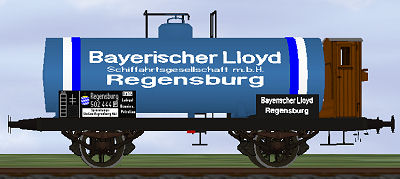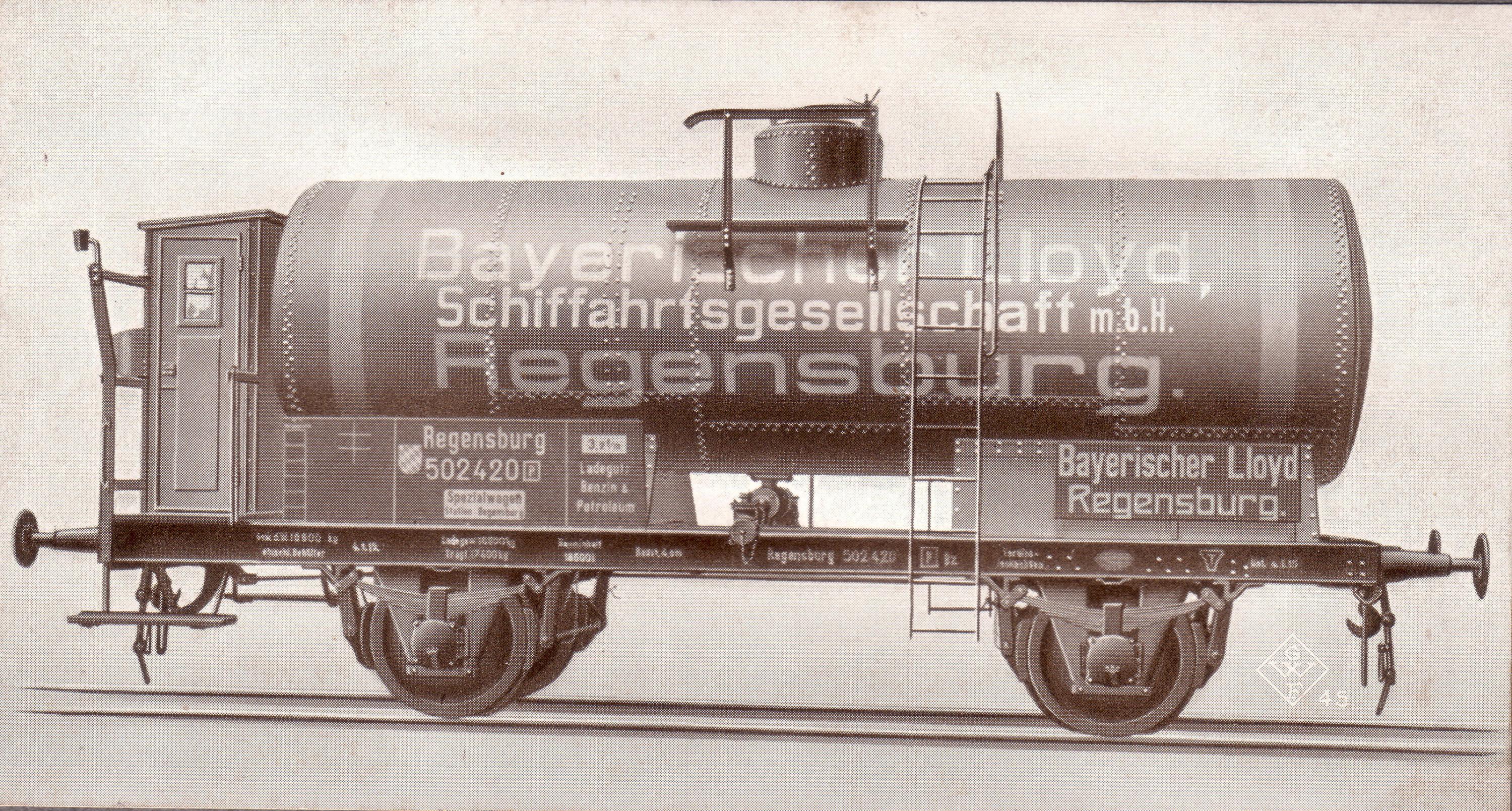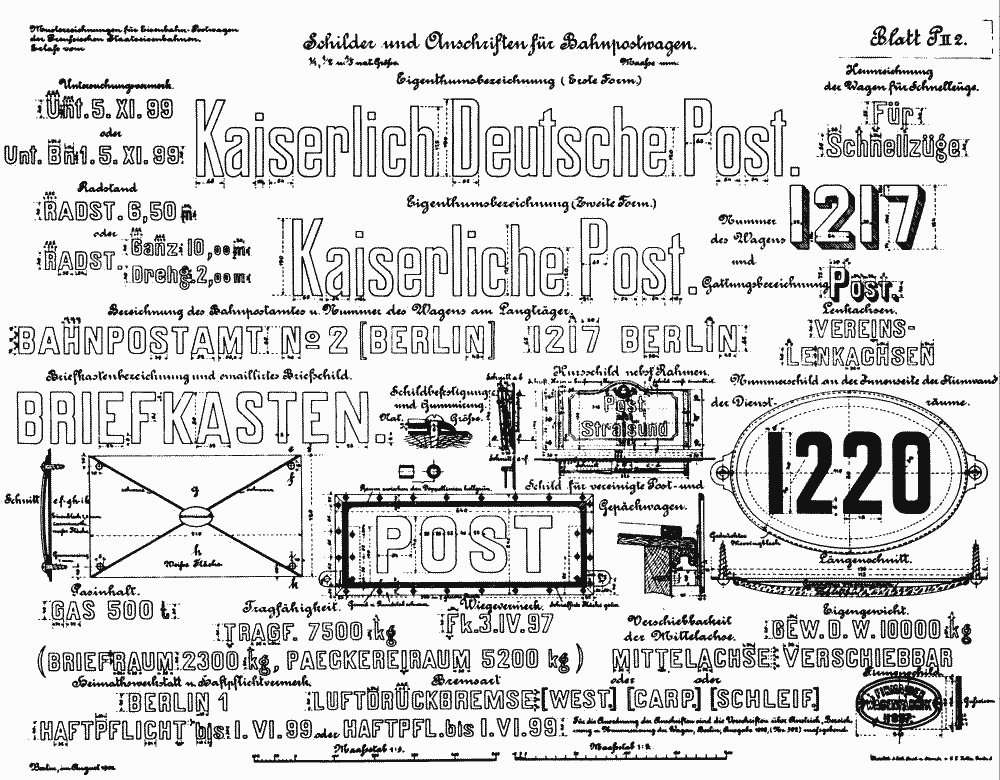
Schriftarten auf Kesselwagen der Bayerische Lloyd , ca. 1920(?)
kann mir jemand bei der Identifikation der verwendeten Schriftarten auf dem abgebildeten Kesselwagen behilflich sein? Bei den Beschriftungen am Rahmen und dem linken Stehblech unterhalb des Kessels tippe ich auf DIN1451, der Kessel selbst und das rechte Stehblech sind jedoch mit mindestens zwei unterschiedlichen Schriftarten versehen, die ich nicht identifizieren kann. Bei der oberen hatte ich Franklin Gothic vermutet, dort passt jedoch das r und einiges Andere nicht. Ich würde mich sehr freuen, wenn mir hier jemand weiterhelfen kann!
Für solche Anschriften auf Bahn-Fahrzeugen wurden damals Musterzeichnungen von Grafikern angefertigt, und als verbindlich festgelegt. Schildermaler mussten dann im Rahmen des damals technisch möglichen diese Vorlagen auf die Fahrzeuge übertragen.
Eine solche Musterzeichnung sah dann so aus:
Leider sind die meisten dieser Musterzeichnungen verloren gegangen, Möchte man also die Schrift doch digitalisieren, bleiben nur die vorhandenen Abbildungen und oft ein gehöriges Maß an Phantasie, sich in den Stil des damaligen Grafik-Kollegen hinzudenken.
Vielen Dank für Eure Antworten. Ich möchte die Schrift nicht digitalisieren, die Beschriftung allerdings schon. Das lässt sich ja auch ohne entsprechenden Font machen. Die Musterzeichnungen liegen sicher für die bahninternen Beschriftungen der Fahrzeuge zugrunde, ob man sich aber auch für die eher werblichen Firmenaufschriften an solche Musterzeichnungen gehalten hat? Interessant finde ich, wie flexibel Schrift verwendet wurden, wenn man sich z.B. das "Regensburg" unten rechts anschaut, das von den anderen Beschriftungen wieder abweicht.
von wann stammt dieser Kesselwagen und gibt es Angaben zur Farbgebung?
Von wann der Wagen stammt, müsstest du eigentlich selbst erkennen können, denn er ist ja auf dem Bild mit genügend Anschriften versehen, unter anderem 2 Daten: 4. 1. 12 und das Datum der nächsten Prüfung 4. 1. 15.
Die Firma Bayrischer Lloyd wurde 1913 gegründet.
Was die Farbgebung anbelangt, kann ich jedoch nur Mutmaßen:
Auf dem Wagen befindet sich ja dieses Bayrische Rauten-Wappen, in Weiß-Blau, dies wird wohl im typisch bayrischen Weiß/Himmelblau ausgeführt worden sein. Da der Schriftzug Bayrischer Lloyd und Regensburg auf dem Kessel eine ähnliche Helligkeit wie das Blau des Wappens hat, wie auch die beiden Gürtelbänder auf dem Kessel, nehme ich an, dass auch diese Schrift in diesem bayrischen Blau ausgeführt wurde, ebenso die beiden Bänder um den Kessel, die anderen Anschriften werden wohl in weißer Farbe erstellt worden sein. Das Bremserhäuschen war wohl aus Holz, das dann sehr wahrscheinlich mit Carbolineum behandelt worden war, also typisches Güterwaagen-Dunkelbraun.
Kessel, wie auch der Wagenrahmen bekam damals oft folgenden Lackaufbau, der dann mit dem Lackierdatum und der ausführenden Firma oft auch als kleine Anschrift irgendwo am Rahmen angebracht wurde:
Grundierung Bleimennige, Füllerschicht in Hellgrau, erste Lack-Zwischenschicht Albertol rostbraun, zweite Albertol schwarz (2 Farben, um die vollständige Beschichtung jeweils optisch prüfen zu können), darauf die Wetterschutzschicht aus dunkelgrauer Eisenglimmerfarbe . Albertol war ein im wesentlichen noch auf Leinöl mit Phenol-Formaldehyd-Harz hergestellter Öl-Lack mit Pigmenten und Füllern aus gemahlener Kupferschlacke oder Ruß.
Ich habe eine detailierte Vorschrift und Auflistung der Arbeitsschritte, Lacke, Materialien und Einsparungen für die Kriegslok BR 52 aus der Industrie-Lackier-Betrieb von 1943. Bei Interesse könnte ich das kopieren.
Um ehrlich zu sein, ich habe jemanden Gefragt, den ich kenne, durch die Schriften für Eisenbahnen, die ich erstellt habe (von dem hab ich auch diese Musterzeichnungen) Und ja, auch daran bin ich interessiert, eventuell kann ich dem, der mit hier geholfen hat auch weiterhelfen :-)